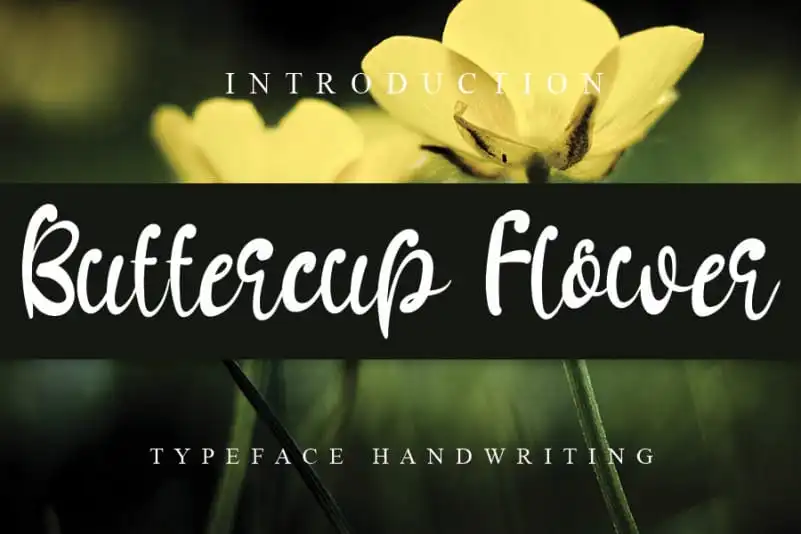
A Buttercup Flower Font é uma elegante e delicada tipografia feita à mão, sua característica mais marcante são as letras arredondadas e distintas que a tornam uma verdadeira obra de arte. Suas linhas perfeitamente redondas e os traços precisos fazem dela um recurso visual único. Este font é tão versátil quanto encantador, criando designs impressionantes para qualquer projeto. Descubra o charme inconfundível desta fonte à mão e explore seu poder em tornar seus trabalhos ainda mais singulares. Perfecta para quem busca um toque de elegância e originalidade em cada obra que cria.